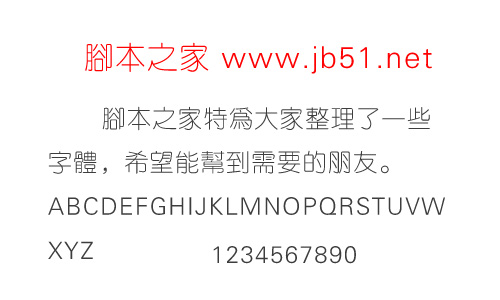
方正細圓繁體字體是方正字體庫中的一種字體,方正圓體家族的中宮寬松,字面大,起筆處與收筆處為圓形,折筆處呈圓弧狀。方正圓體家族的字形風(fēng)格舒展柔和,適用于女性、兒童和生活用品類的宣傳冊和包裝設(shè)計等。方正圓體家族包括3款字重,其中方正粗圓筆畫厚重飽滿,適用于標(biāo)題;方正準(zhǔn)圓筆畫粗細適中,適用于正文排版;方正細圓筆畫纖柔,也適用于正文排版。喜歡的朋友們可以前來下載使用。